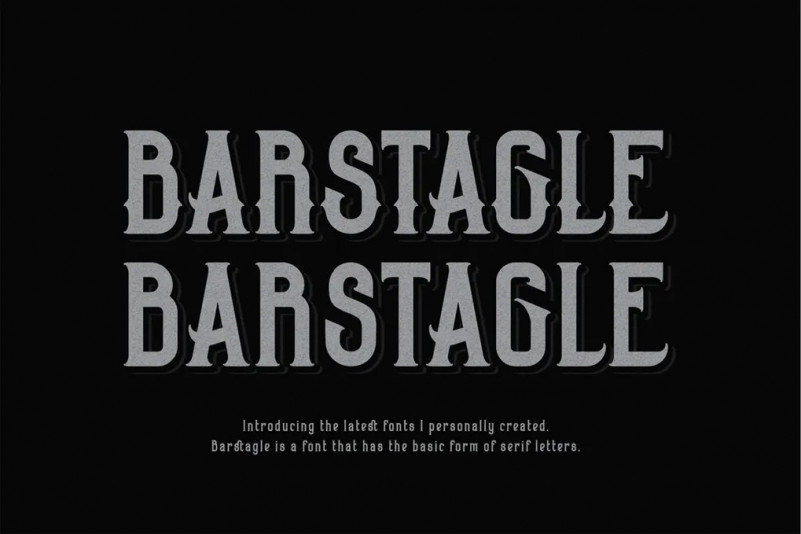
Barstagle Font
BARSTAGLE est une police Serif, avec une légère touche gothique à la famille régulière. Barstagle est parfait pour les titres et le corps du texte. Également idéal pour fabriquer des logotypes, des badges, des étiquettes d’alcool, des couvertures de magazines, des titres de paragraphes ou comme paragraphes.
Barstagle est disponible en 2 versions, régulière et unthorns, vous pouvez voir la différence dans la section aperçu de couverture de cette police. Se compose de majuscules, minuscules, chiffres et ponctuation, ainsi que de nombreuses ligatures standard et ligatures discrétionnaires en tant que partisans de la lettre majuscule. Et beaucoup de caractères alternatifs sur la grande mêlée aussi.